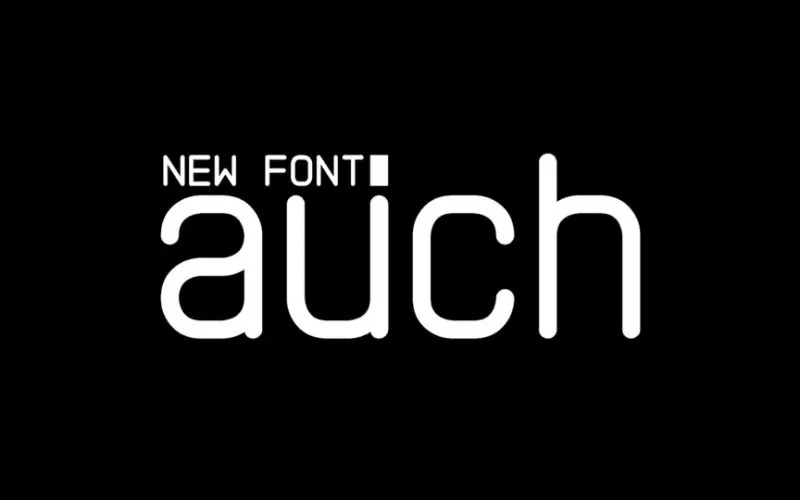
Introduzimos Auch Free Font, uma moderna tipografia sans serif com linhas contornadas que se destaca pela sua aparência ousada e limpa. Ela é perfeita para aplicações de título, design de logotipos, criação de gráficos de venda e mesmo para nomes em larga escala utilizados em assinaturas de sandwich boards, painéis de vitrines ou bandeiras. Auch Free Font foi projetada para chamar a atenção e é uma ótima opção para qualquer necessidade que exija destaque. Suas linhas finas e os contornos elegantes permitem um resultado visual sofisticado sem perder a modernidade que tanto valorizamos em nossa era digital. A fonte foi criada por Hamilton, com uma forte foco na simplicidade e no brilho contemporâneo das formas. Esta fonte é ideal para quem busca um design clean que se destaca do resto e tem o poder de comunicar efetivamente através de qualquer plataforma visual.